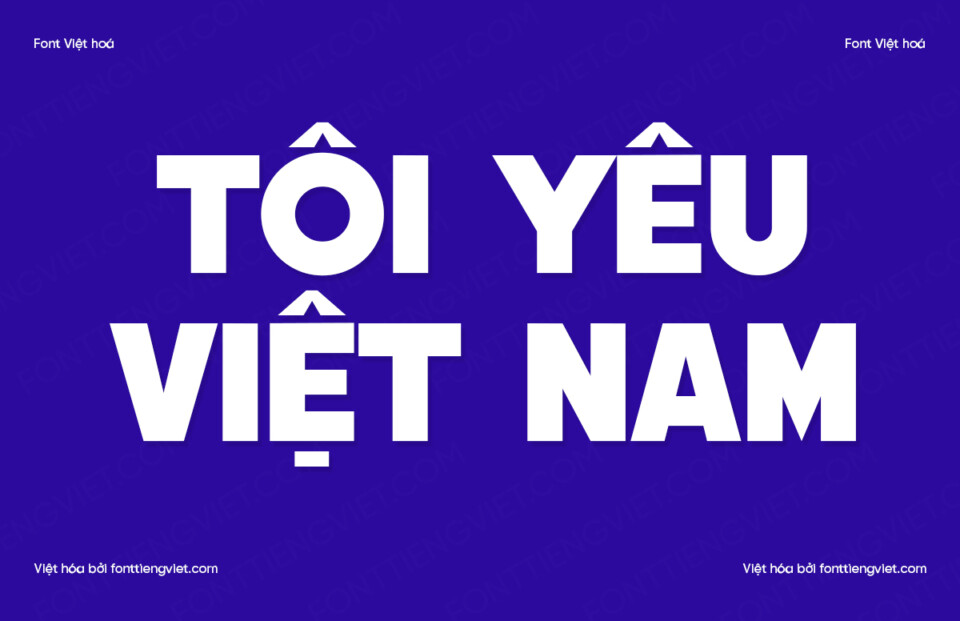
Font Việt hóa 1FTV VIP Edges
Giới thiệu về bộ Font Việt hóa 1FTV VIP Edges chuyên nghiệp
Trong thế giới đồ họa hiện đại, việc lựa chọn một bộ Font Miễn Phí chất lượng đóng vai trò then chốt giúp tác phẩm trở nên nổi bật và truyền tải đúng thông điệp. Một trong những cái tên đang được cộng đồng thiết kế tại Việt Nam săn đón nồng nhiệt chính là Font Việt hóa 1FTV VIP Edges. Đây là một bộ phông chữ sở hữu phong cách thiết kế độc đáo với những đường nét sắc sảo, hiện đại và vô cùng tinh tế. Phiên bản Việt hóa này giúp các bạn học sinh, sinh viên và những người làm sáng tạo nội dung dễ dàng sử dụng trong các bài thuyết trình, dự án cá nhân hoặc các ấn phẩm truyền thông mà không lo về lỗi hiển thị dấu tiếng Việt. Sự xuất hiện của 1FTV VIP Edges mang đến một làn gió mới, phá bỏ sự rập khuôn của những kiểu chữ truyền thống cũ kỹ.
Đặc điểm nổi bật của Font Việt hóa 1FTV VIP Edges
Phong cách thiết kế hình khối mạnh mẽ
Đúng như tên gọi Edges, bộ font này tập trung khai thác các góc cạnh vuông vức nhưng không kém phần thanh thoát. Mỗi ký tự trong Font Việt hóa 1FTV VIP Edges được chăm chút tỉ mỉ để tạo ra sự cân bằng giữa thị giác và tính ứng dụng. Các nét chữ dày dặn giúp tạo độ nhận diện cao, cực kỳ phù hợp cho các tiêu đề lớn, banner quảng cáo hoặc làm logo thương hiệu. Khi kết hợp với các tông màu tương phản, bộ font này sẽ tạo nên hiệu ứng thị giác cực kỳ mạnh mẽ, thu hút người xem ngay từ cái nhìn đầu tiên.
Khả năng tối ưu cho tiếng Việt hoàn hảo
Một trong những ưu điểm lớn nhất của phiên bản này chính là việc xử lý dấu câu cực kỳ mượt mà. Đội ngũ thực hiện đã tinh chỉnh để các dấu thanh không bị đè lên chữ hoặc quá xa rời ký tự gốc, giữ được tính thẩm mỹ nguyên bản của thiết kế quốc tế. Người dùng có thể hoàn toàn yên tâm khi soạn thảo văn bản dài mà vẫn đảm bảo được sự đồng nhất và chuyên nghiệp trong từng dòng chữ.
Ứng dụng thực tế của Font Việt hóa 1FTV VIP Edges
Sử dụng trong giáo dục và học tập
Đối với các bạn học sinh và giáo viên, việc sử dụng phông chữ này trong các slide bài giảng hoặc báo cáo thực tập sẽ giúp nội dung trở nên hiện đại và dễ tiếp thu hơn. Nó giúp các tiêu đề chương mục rõ ràng, mạch lạc, hỗ trợ tốt cho việc ghi nhớ thông tin. Ngoài ra, các câu lạc bộ trong nhà trường cũng có thể dùng font này để thiết kế poster sự kiện hay áo đồng đẳng cấp.
Sáng tạo nội dung trên mạng xã hội
Với sự bùng nổ của các nền tảng video và hình ảnh, 1FTV VIP Edges là lựa chọn tuyệt vời để làm phụ đề hoặc chèn chữ vào ảnh nền. Độ đậm nhạt vừa phải của font giúp chữ không bị chìm lấp bởi hình ảnh minh họa, từ đó nâng cao giá trị cho các sản phẩm truyền thông số của bạn.
Kết luận về bộ phông chữ 1FTV VIP Edges